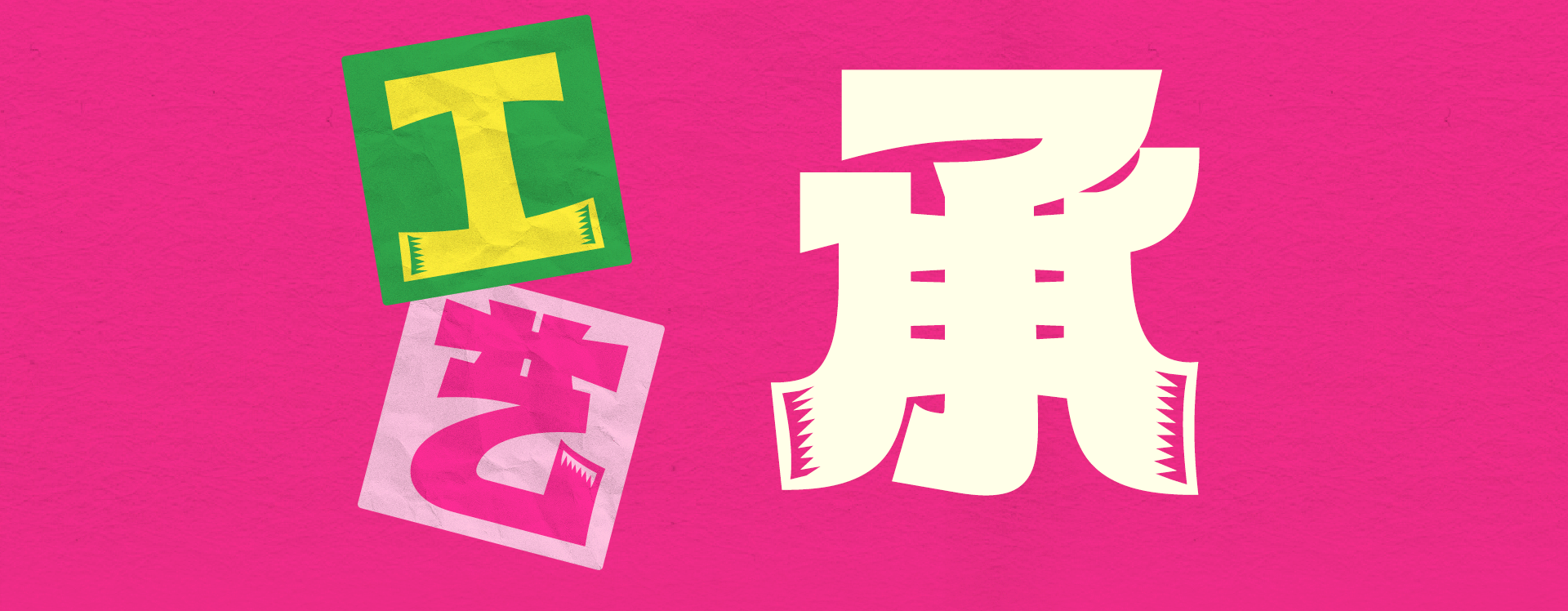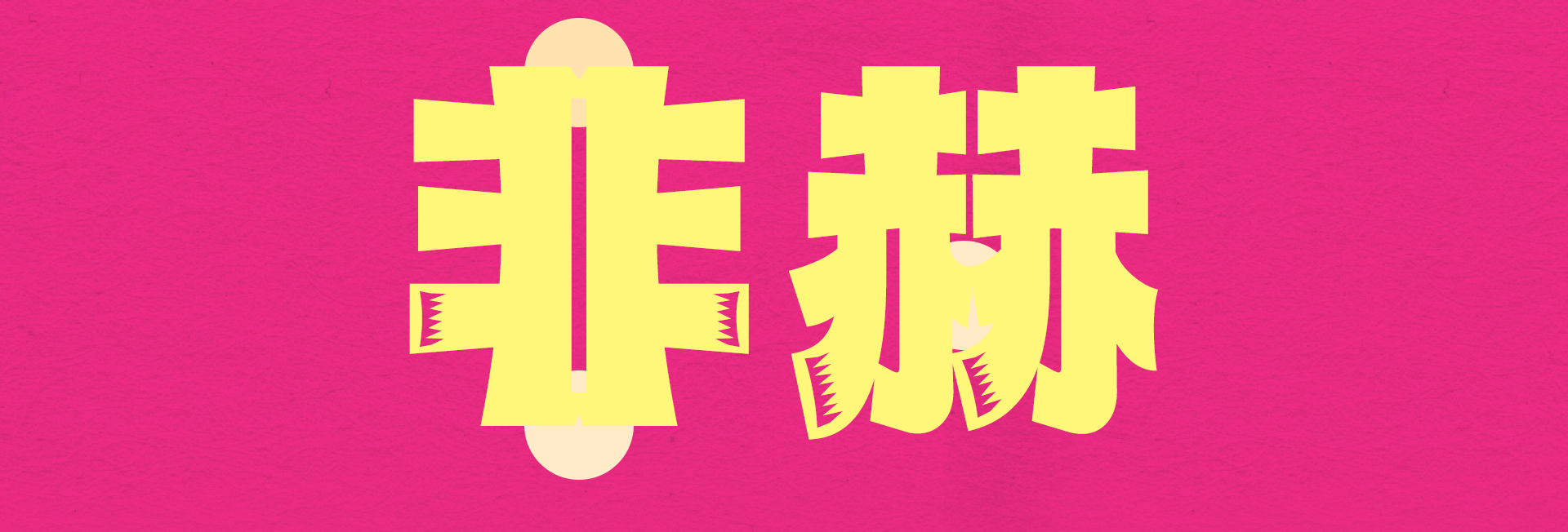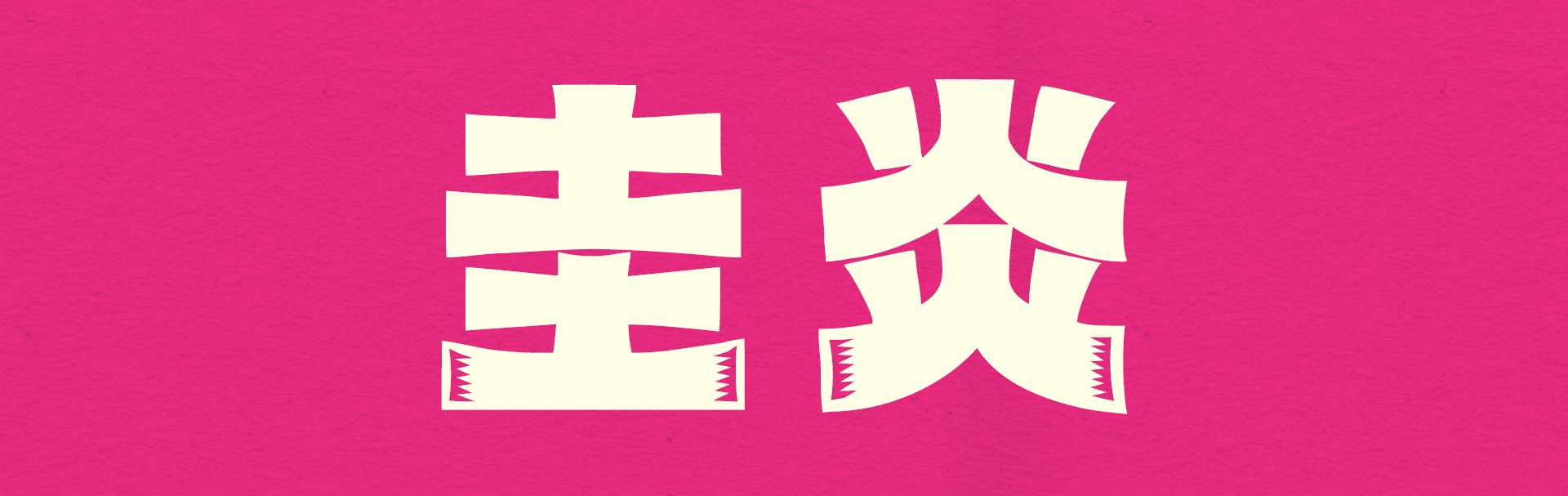
贺兰石,宁夏“蓝宝”
以宁夏省级非遗传承人何立宁为代表的工匠大师,致力于传承贺兰石印章雕刻技艺
其中,何立宁老师凭借精细刀工、新颖俏色、传统与现代相结合的作品,蜚声本土内外
持刀向石,不止于印
如同何立宁老师对篆刻艺术的独到理解
字魂以石刻融入字体设计,唤醒灵感新意
「字魂印石体」,由此诞生
从2018年以来,字魂始终致力于用汉字文化赋能多元领域
并与吴文化博物馆、北京民艺非遗研究院、華豊铸字等机构达成合作
用定制字体诠释非遗之美
妙手绘新,生机万象
我们相信,当手艺从器物走向生活,当美学从收藏走向大众
非遗便将真正走进人们的日常点滴,焕发与时俱进的无穷魅力